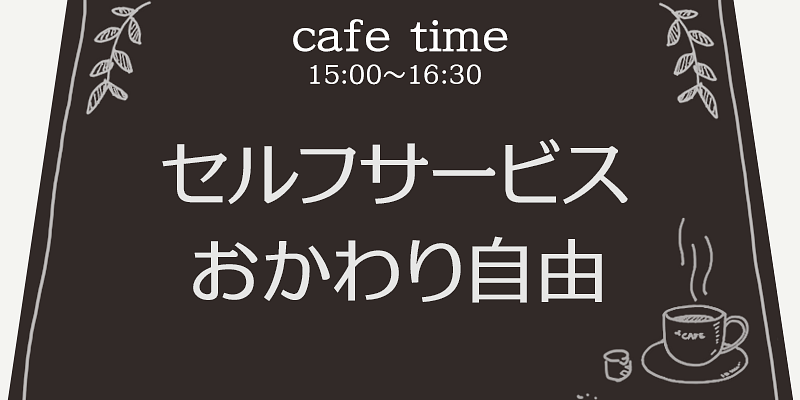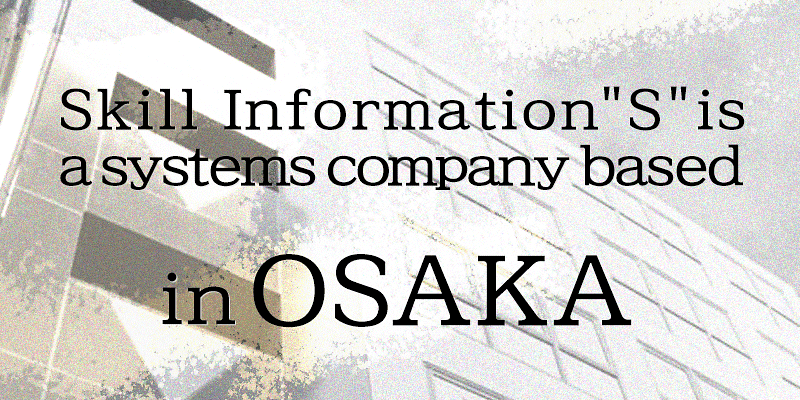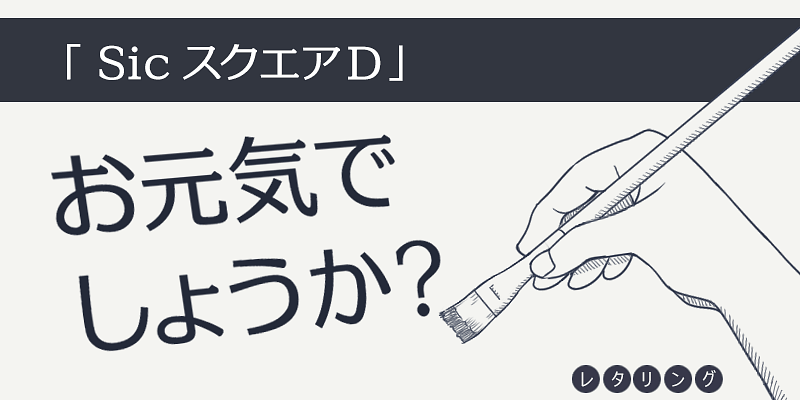
De lettertypen die zijn gemaakt door wijlen Takeharu Suzuki, werden ontwikkeld op basis van zijn uitgebreide ervaring, variërend van belettering tot bitmaplettertypen, tekstverwerkingslettertypen en penseelschriftlettertypen. In het bijzonder streefde hij naar een ‘stressvrij gothic lettertype voor horizontale tekst’, wat leidde tot de ontwikkeling van het zeer goed leesbare ontwerp van het standaard Windows-lettertype, Meiryo.
De diversiteit van zijn lettertypeontwerpen strekt zich niet alleen uit tot warme, handgeschreven penseelschriftlettertypen en basislettertypen, maar ook tot gothic, gestileerde en displaylettertypen. Zijn lettertypen kunnen worden gebruikt voor een breed scala aan toepassingen, waaronder advertenties, video’s en digitale media. Ze bieden een gevoel van originaliteit en zijn geliefd bij velen.
Skill Information”S” kwam in 2007 in de lettertypewereld terecht dankzij de samenwerking met Techno Advance Co, Ltd. en staat bekend om zijn focus op softwareontwikkeling, met name voor de gezondheidszorg.